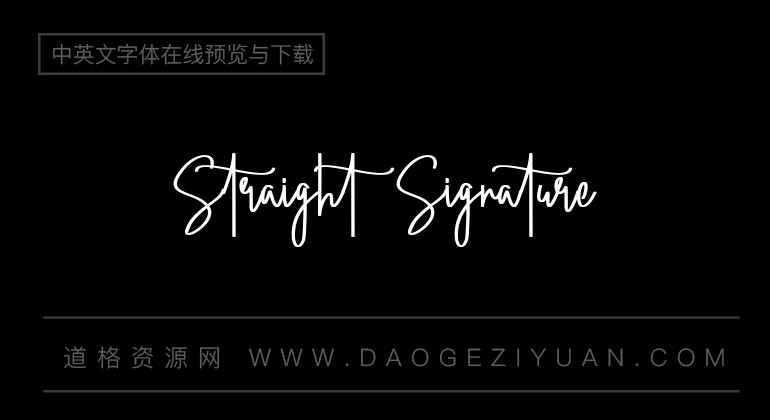
Straight Signature
Straight Signature 是一款手写体字体,它特别适合用于各种社交媒体、广告、海报、品牌标识等场景。Straight Signature 字体具有细腻的笔触,优雅的曲线,以及自然的行距,能够为任何文字提供清晰、精致的外观。此外,它还具有全英文字符集,可以满足各种不同的语言需求。
Straight Signature是一款非常不错的手写艺术字体,具有很好的视觉感,适合于文化类的宣传设计、商业类品牌的广告和产品包装设计以及个性化文字排版等较多场景。